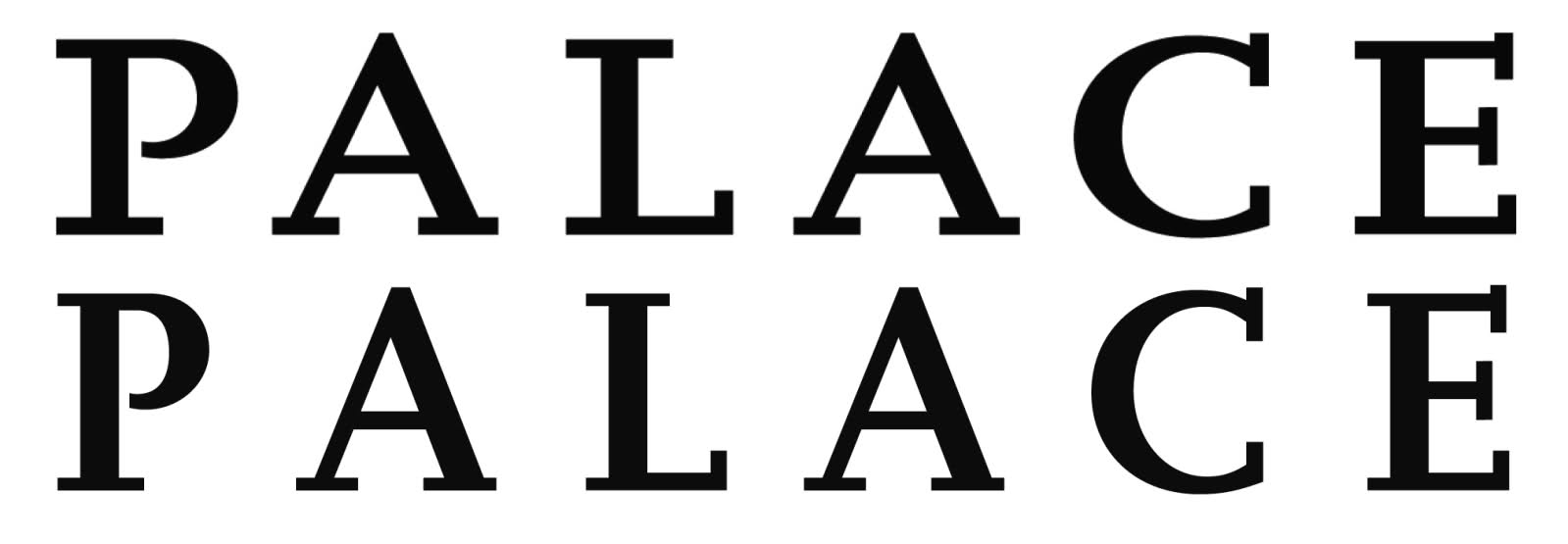
Schrift ähnlich der Scala Bold gesucht …
oben die gesuchte
unten zum Vergleich die Scala Bold
Ich dachte erst, dass die gesuchte nur verzerrt ist, aber die Serifen sind dicker als bei der Scala …
Small Caps :-?
Könnte sein … sind die breiter oder wurde der Schriftzug verzerrt? Ich hab die SC nicht und kann es nicht prüfen.